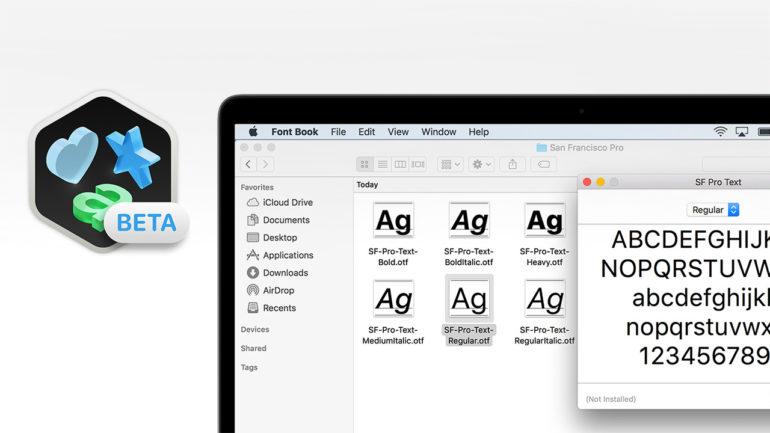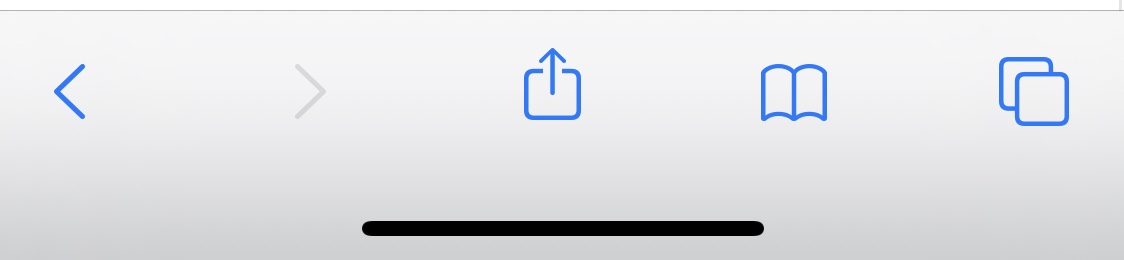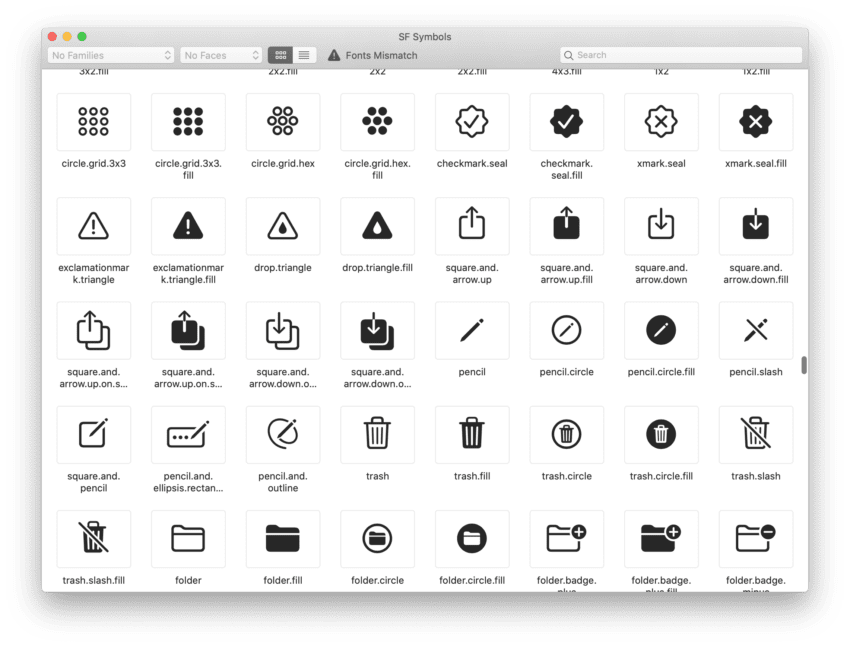
Apple introduce l’app SF Symbols e due nuovi Font: San Francisco Rounded e New York
Con il rilascio della prima beta di iOS 13, Apple ha aggiornato anche le proprie Risorse di Design, pubblicando SF Symbols, un set di 1500 simboli da installare sui Mac insieme ai font San Francisco e che possono essere utilizzati nelle applicazioni e nei Mockup grafici.
Gli SF Symbols di Apple sono pensati per funzionare con il font di sistema San Francisco e quindi assicurano un perfetto allineamento verticale quando vengono posti accanto ad un testo.
Come avevamo già notato in un articolo pubblicato su iSpazio, alcune applicazioni (come Safari ma anche altre), mostrano dei simboli più piccoli, leggermente più arrotondati negli angoli e con uno spessore maggiore.
Apple ha effettivamente cambiato tutti i simboli e le icone presenti in iOS 13 e le ha racchiuse in questo pacchetto da 1500 risorse.
Ogni simbolo è disponibile in 9 varianti, dallo spessore differente. Si parte dall’UltraLight fino ad arrivare al Black ed ognuna di queste varianti corrisponde perfettamente allo spessore dei font San Francisco (solitamente espresso con un weight che va da 100 a 900). Ogni simbolo è anche disponibile in 3 dimensioni da utilizzare in base alla posizione che ricopriranno nelle app.